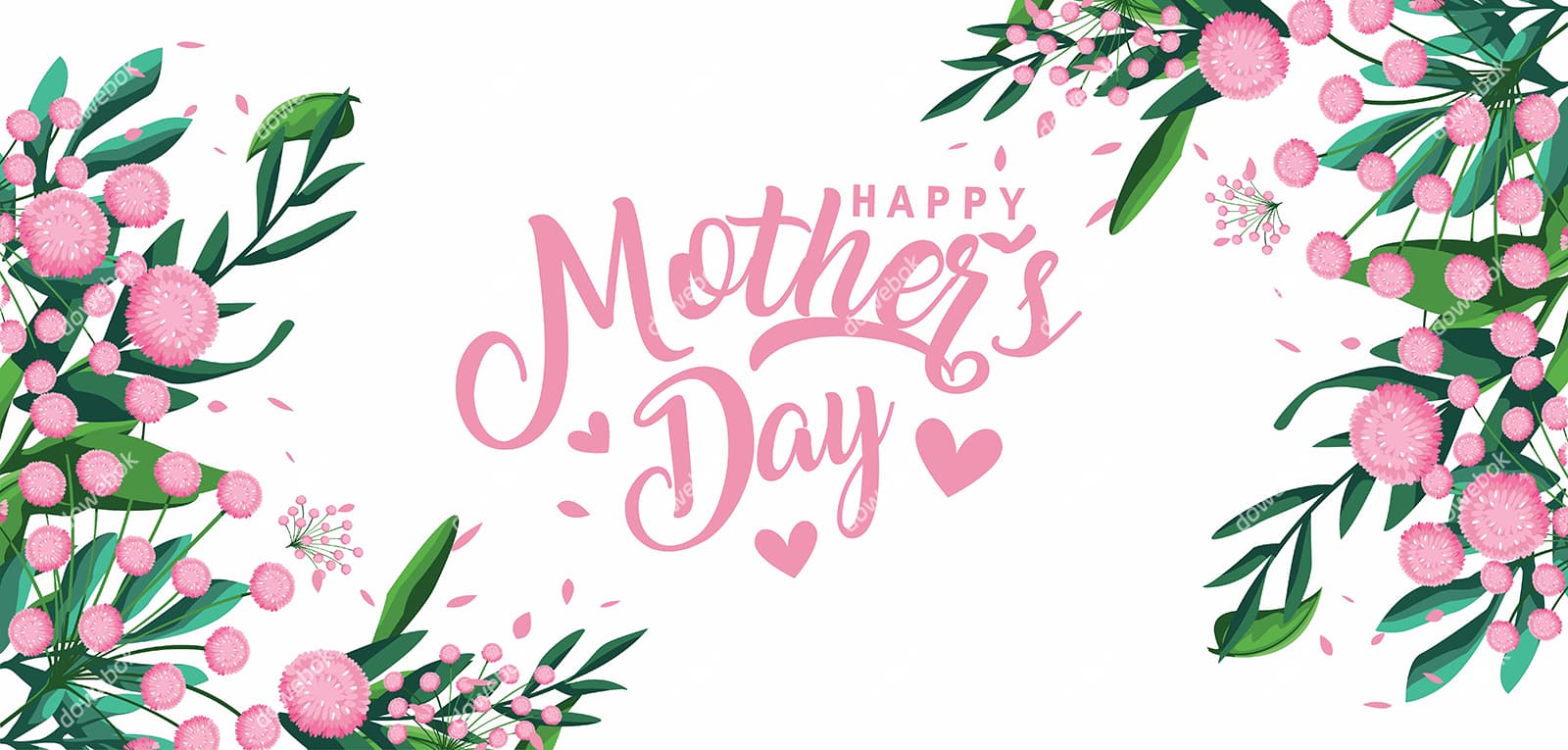
这是一款由粉色花朵和 happy mother’s day 字母设计的母亲节矢量素材,图片以白色为背景,中央是用粉色手写字体写的 “Happy Mother’s Day”,文字间点缀着几个粉色小心形图案。画面左右两侧是绿色枝叶搭配粉色绒球状花朵的装饰,花朵与枝叶错落有致,整体营造出清新、温馨的母亲节氛围,传递出对母亲的美好祝福。